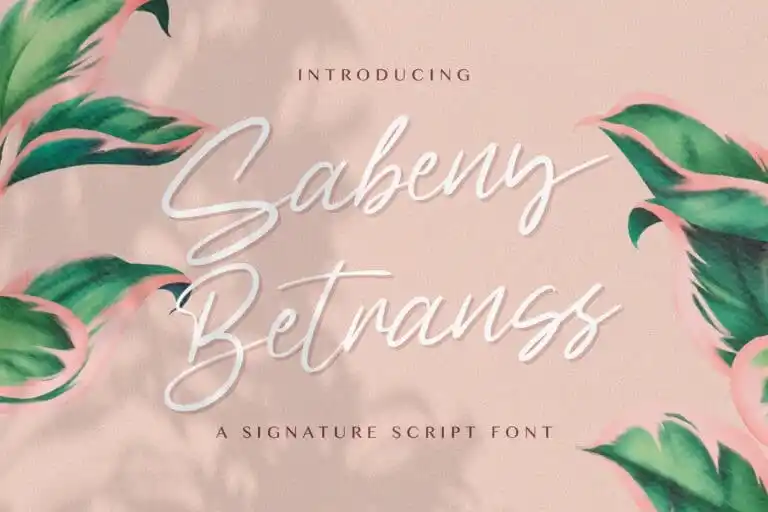
Sabeny Betranss Script Font – Download Grátis
Aproveite a introdução do Sabeny Betranss Script Font, uma elegante e moderna fonte cursiva que vai enriquecer seus designs tipográficos com charme e sofisticação. Com sua composição de caracteres bem equilibrados e um aspecto delicado, esta fonte é uma escolha perfeita para projetos criativos que buscam aperfeiçoar a qualidade visual de suas idéias. Sua simplicidade ainda mantém um toque intrigante e moderno, fazendo dela uma opção versátil. Ela combina harmoniosamente com diversos estilos, desde designs vintage até trabalhos contemporâneos. Adicione o Sabeny Betranss Script Font a seu próximo projeto, observe como ele dá vida às suas ideias mais inovadoras e criativas. Essencial para designers que buscam incorporar um toque sofisticado em seus projetos, esta fonte oferece uma ótima opção para manter seus designs únicos e imprimíveis. O Sabeny Betranss Script Font é a escolha ideal para quem busca uma tipografia moderna e encantadora, que se destaca em qualquer projeto de design gráfico.